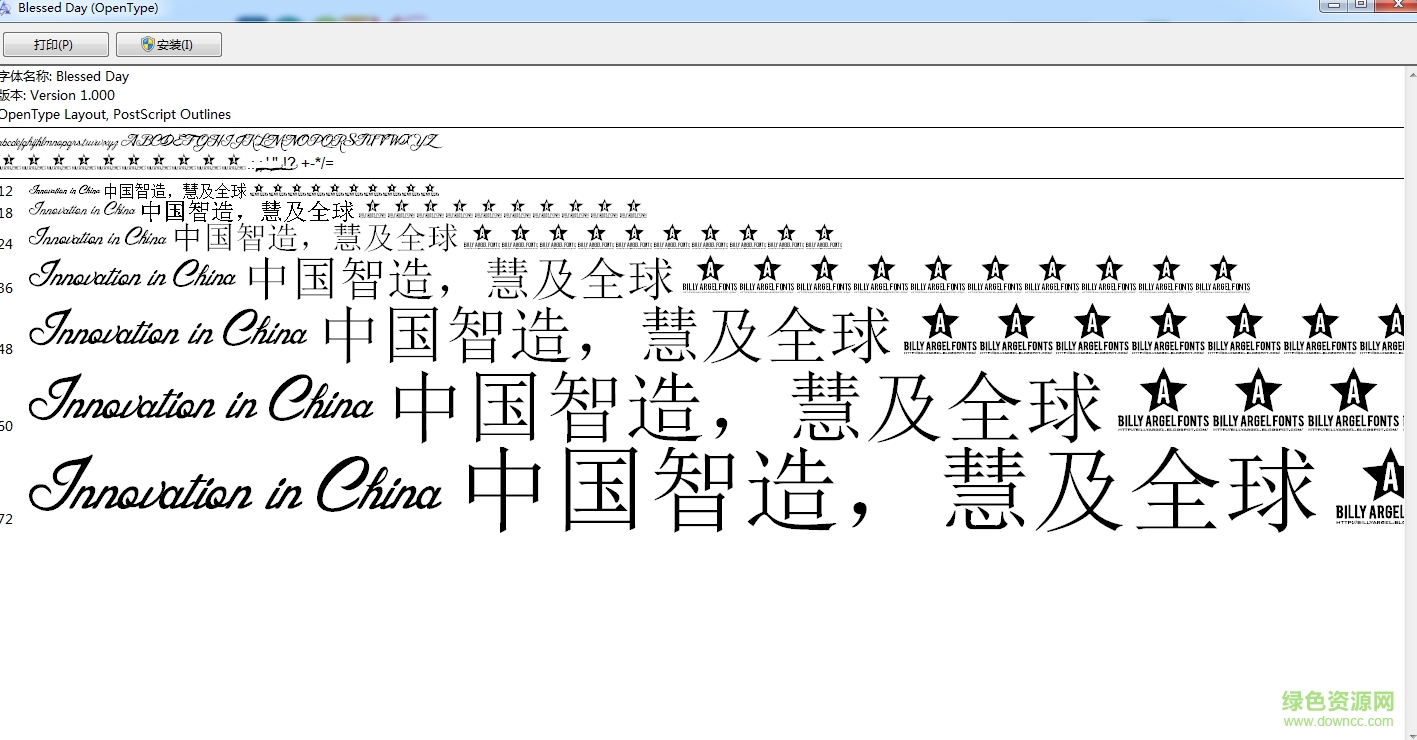
blessed day
blessed day字體是一款優(yōu)雅好看的花體字體,字體華麗線條優(yōu)美,常常用于制造邀請函、精美的賀卡以及各類請柬等,喜歡這款字體的朋友還有在綠色資源網(wǎng)下載!
花體字體特色
1.粗細(xì)變化
2.游絲
3.排版
總的來說即為裝飾性強(qiáng)。